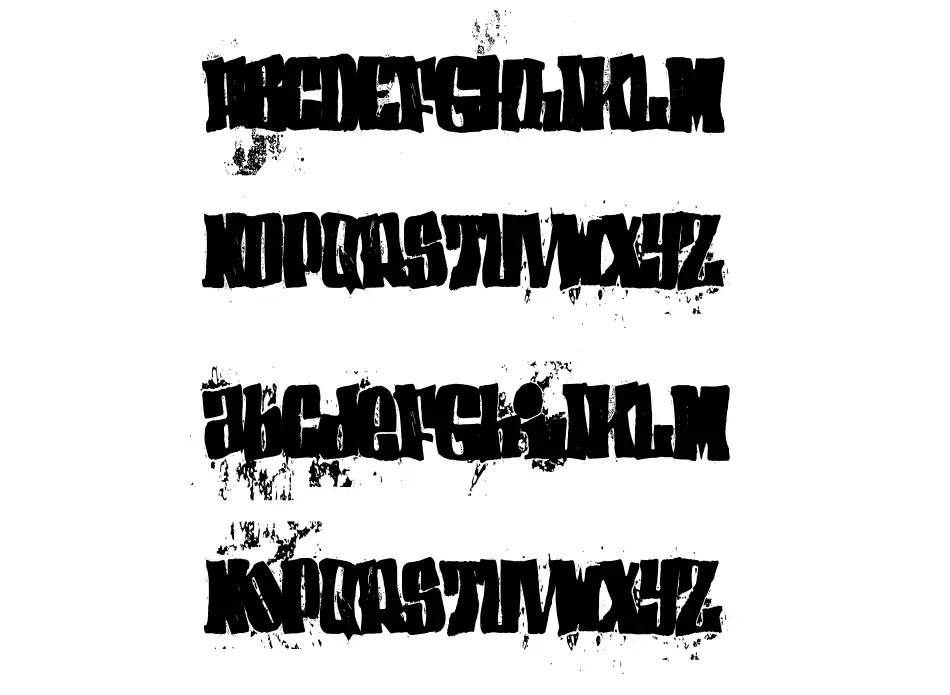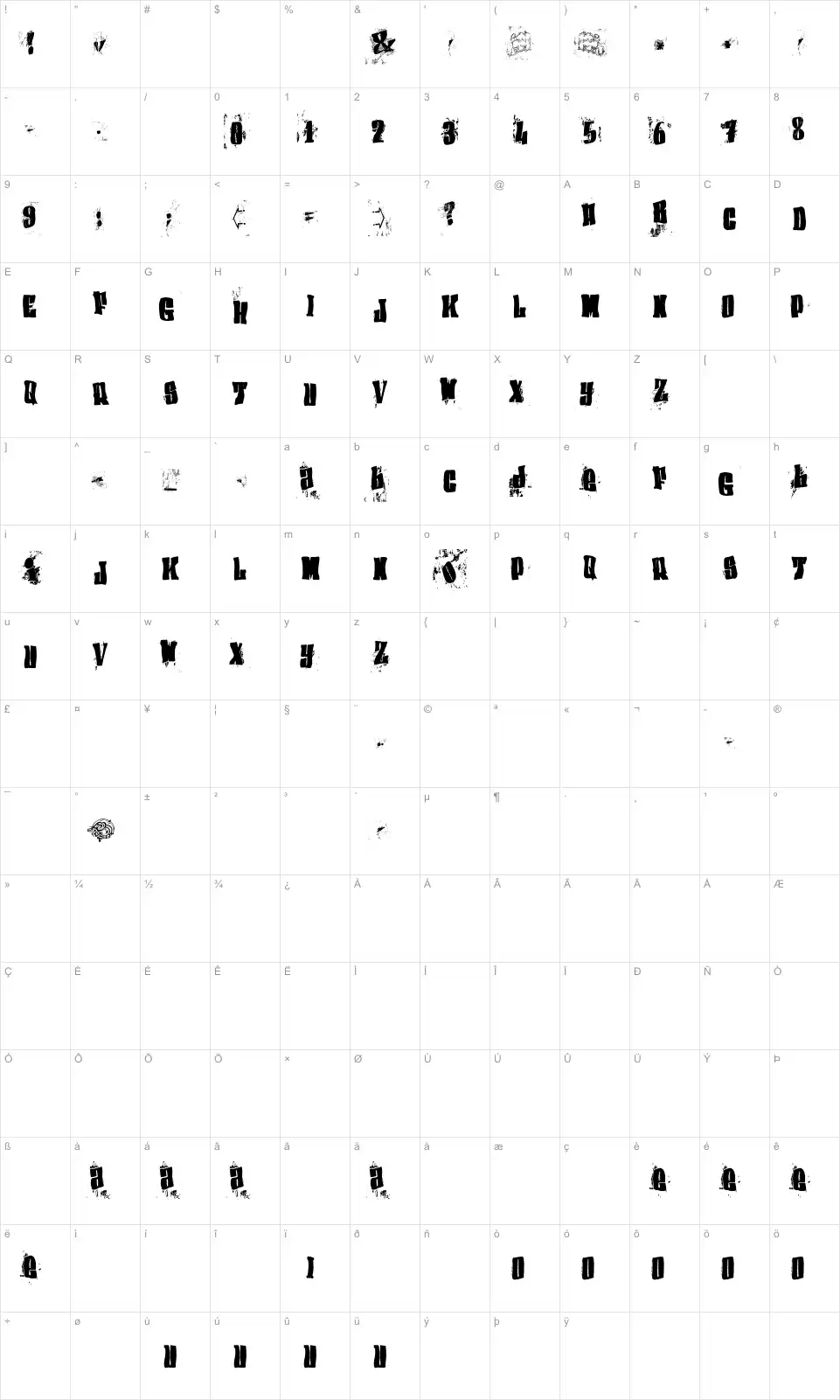
A fonte (el&font BLOCK), criada pelo designer Jérôme Delage, é perfeita para aqueles que buscam um estilo de letra moderno e inovador. Se você está procurando pela (el&font BLOCK) e precisa dela agora, você pode facilmente download a font ou gerar um previsível texto personalizado online para ter uma ideia de como ela vai se assemelhar antes de utilizá-la. Esta font pertence à categoria Script e tem um estilo graffiti, tornando-a ideal para uso em designs digitais modernos e criativos. A fonte foi adicionada em 11 de julho de 2022 e já foi baixada por 10.251 usuários. Com um tamanho de 176 KB, ela é compacta e fácil de integrar em projetos de qualquer tamanho. Além disso, a fonte está licenciada sob o modelo de software por doação, oferecendo flexibilidade e liberdade para os usuários adaptarem e modificarem conforme necessário.
Categoria: Script › Graffiti
Designer: Jérôme Delage